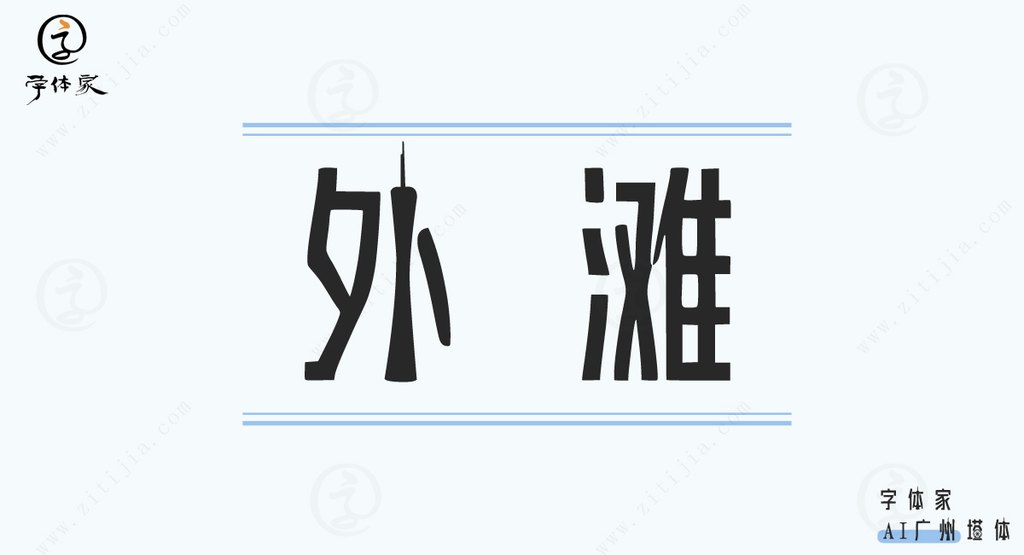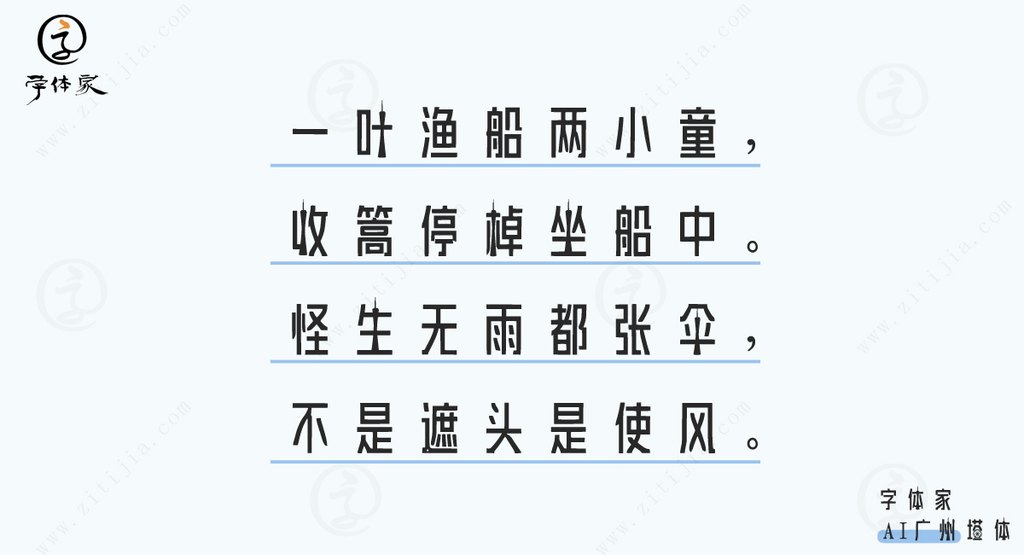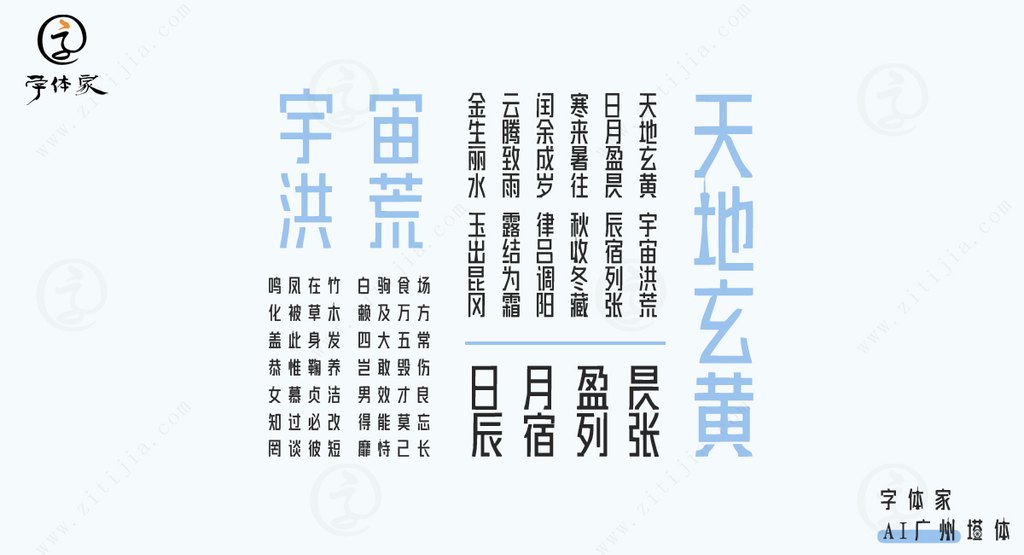
字体家AI广州塔字体:艺术与建筑的完美融合
在字体的世界中,如何将传统印刷字体与城市建筑特色完美结合?答案就在字体家AI广州塔字体。这款字体不仅继承了利索印刷字体的时尚美观,还巧妙地融入了广州塔的建筑剪影,使每个文字更具艺术感和独特性。
灵感来源:广州塔的流动之美
广州塔,作为广州的地标建筑,以其优美的曲线和流线型设计吸引了无数人的目光。字体家AI广州塔字体正是从这一建筑中汲取灵感,将部分“竖”笔画转化为广州塔的剪影,形成了字体与建筑的对话,也让文字充满了现代化的气息。
视觉效果:均衡与魅力的碰撞
这款字体的设计不仅强调广州塔的特色,还在字间距上进行了精密的调整,确保每个文字的视觉效果都是均匀的。这种设计不仅增强了文字的可读性,还为整个页面带来了吸引人的视觉平衡。无论是印刷在纸张上,还是展示在屏幕上,这款字体都能让你的作品瞬间脱颖而出。
应用场景:赋予创意无限可能
字体家AI广州塔字体相当多才多艺,适用于广告标题、平面文案、海报标题、网页广告等多种场合。它不仅能为您的宣传材料增添艺术感,还能将个性和地方特色巧妙地融入其中。想要展现品牌的独特风格和广州的城市魅力,这款字型就是您最好的选择。
城市与字体的交响乐
通过字体家AI广州塔字体,我们不仅欣赏到了文字的艺术之美,也感受到了城市建筑的雄伟。这种设计的巧妙结合,使得每段文字都成了一次建筑与艺术的对话。选择这款字体,就是选择一种新的表达方式,让你的创作更具生命力与城市精神。让我们一起在文字间,探寻广州塔的影子和灵动魅力!